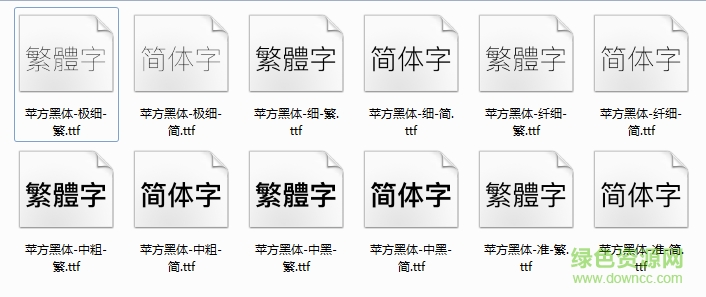
蘋(píng)方字體包含簡(jiǎn)體以及繁體中文,共有12種字體,可以很好地滿足日常設(shè)計(jì)和閱讀的需求!
無(wú)論你是一名設(shè)計(jì)師還是普通用戶,蘋(píng)方字體都能很好地滿足你。蘋(píng)方字體12種字重粗細(xì)為了讓蘋(píng)果的字體可以在 Windows、Android、Linux 等其他平臺(tái)和設(shè)備上使用。
12種字重分別是極細(xì)體、纖細(xì)體、細(xì)體、常規(guī)體、中黑體、中粗體、粗體,全部都是 .ttf 格式使用方法:蘋(píng)方中文字體的英文名稱為「PingFang SC」,在 HTML CSS 里面可以通過(guò) Font-Weight 來(lái)設(shè)置字體粗細(xì)。只要你在 Windows 10 下安裝好蘋(píng)方,那么訪問(wèn)本站應(yīng)該就能看到默認(rèn)是蘋(píng)方的字體效果了。